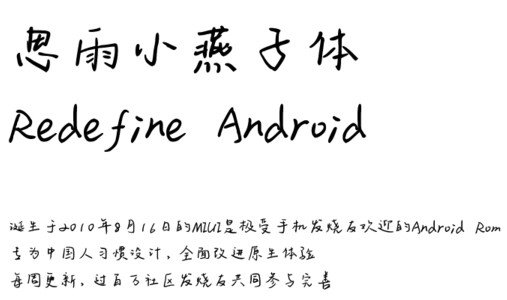
思雨小燕子字體是小米手機(jī)上推出的一款特色手寫(xiě)字體,出自思雨字庫(kù),有著流暢干凈的線(xiàn)條和溫潤(rùn)隨和的筆記,給人十分清晰的視覺(jué)呈現(xiàn),喜歡的朋友就來(lái)綠色資源網(wǎng)試試吧!
思雨小燕子體是在國(guó)家標(biāo)準(zhǔn)簡(jiǎn)體字庫(kù)GB2312所包含6763漢字的基礎(chǔ)上,又增加了近200常用字,已經(jīng)覆蓋了大陸99.75%的漢字使用頻率,足以滿(mǎn)足日常需求。
思雨小燕子體字跡鮮活而清秀,有著極佳的文風(fēng),給大家的藝術(shù)設(shè)計(jì)、平面設(shè)計(jì)、海報(bào)設(shè)計(jì)等都帶來(lái)不錯(cuò)的體驗(yàn),造型疏密結(jié)合,閱讀效果舒適。